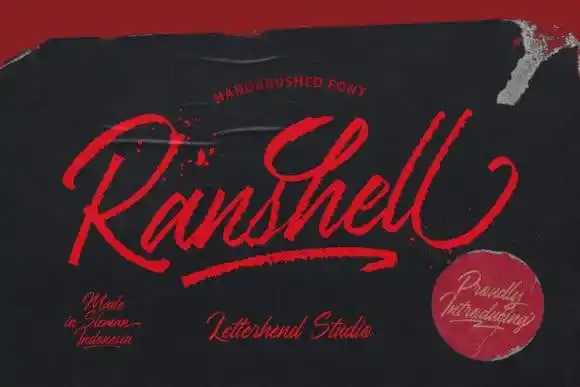
Ranshell Handbrush Font – Download Grátis
A Ranshell Handbrush Font é uma elegante fonte feita à mão que traz vida ao mundo digital, perfeita para os profissionais digitais e artesãos. Esta coleção de scripts é ideal para personal branding, tornando-a versátil para diversos aplicativos. Com seu estilo único e fluido, este script será um toque final em cada projeto que você criar. A Ranshell está encodada conforme PUA, permitindo que você aceda facilmente a todos os símbolos e swashes da fonte. Este aspecto específico torna esta fonte ainda mais versátil para uma ampla gama de usos, seja personal branding, convites de casamento ou publicidade – há algo que essa coleção de tipos autênticos pode ajudar em cada projeto!